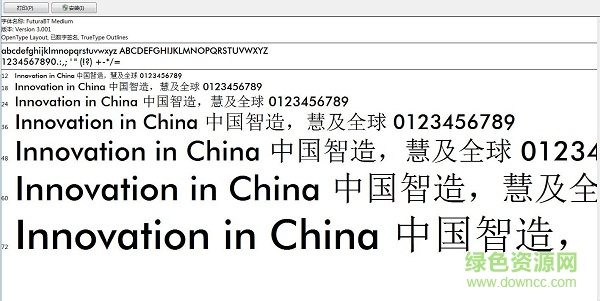
futura bt medium字體是一款新穎活潑的英文無襯線字體,結(jié)體端莊,筆畫工整充滿美感,本站還擁有超多設(shè)計(jì)精美的高品質(zhì)無襯線字體,需要的朋友快來下載吧!
無襯線體(Sans-serif)專指西文中沒有襯線的字體,與漢字字體中的黑體相對(duì)應(yīng)。與襯線字體相反,該類字體通常是機(jī)械的和統(tǒng)一線條的,它們往往擁有相同的曲率,筆直的線條,銳利的轉(zhuǎn)角。